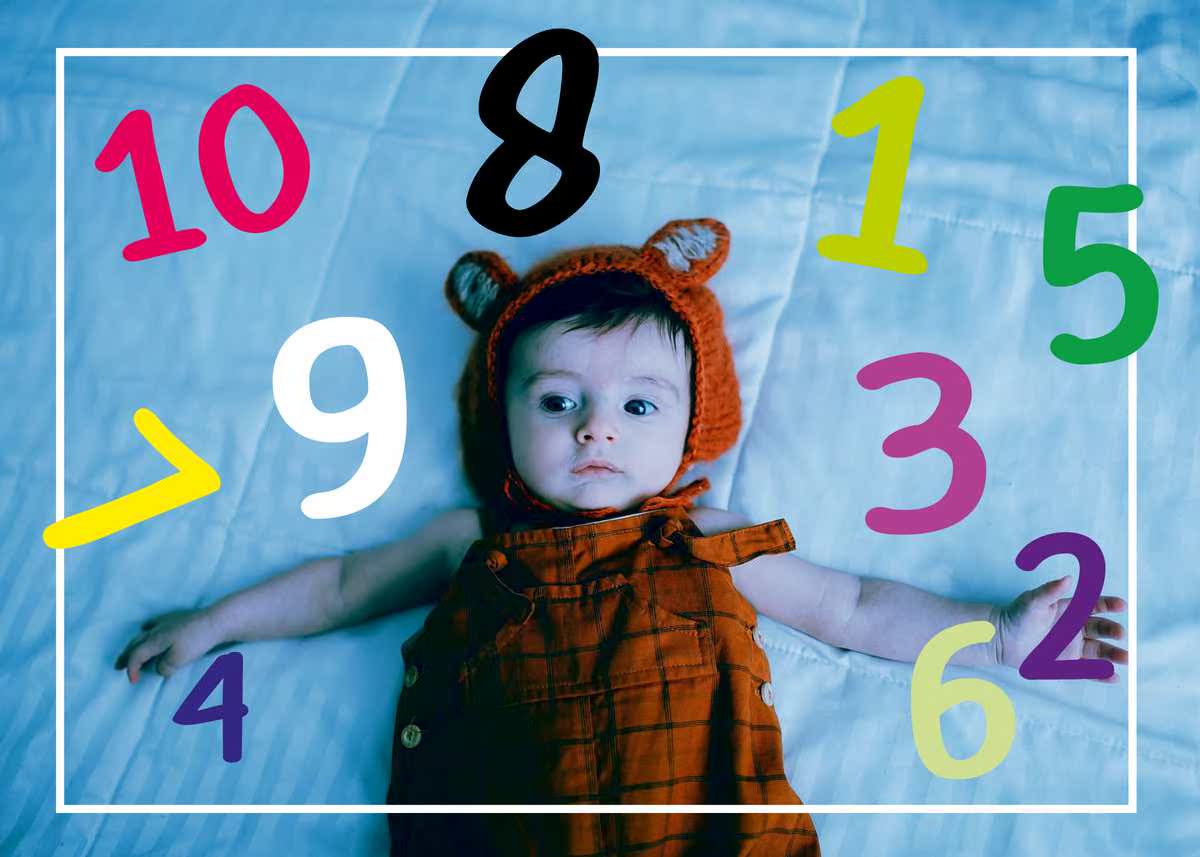
介绍Rotherjanu,Isan和CraftedFont。它包括Reguler、BoldandTalic,包括大写、小写、数字、标点符号,也支持多语言字母。Brotherjanu适用于海报、标题、标识、杂志、品牌、书籍、动态图像、包装、网页、电影或任何奇思妙想。介绍Rotherjanu,Isan和CraftedFont.ItCometherjanu,BoldandTalic,包括大写、小写、数字、标点符号,也支持多语言字母。Brother适用于海报、标题、标识、杂志、品牌、书籍、动态图像、包装、网页、电影或任何突发事件。